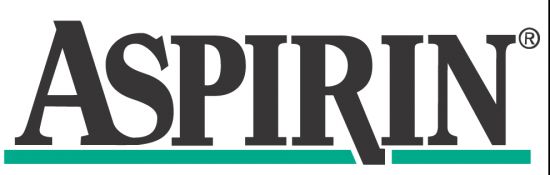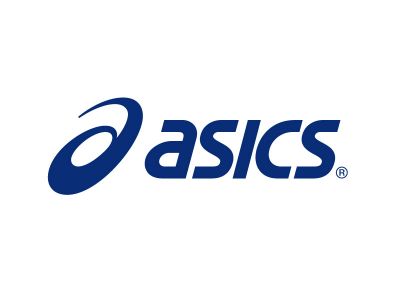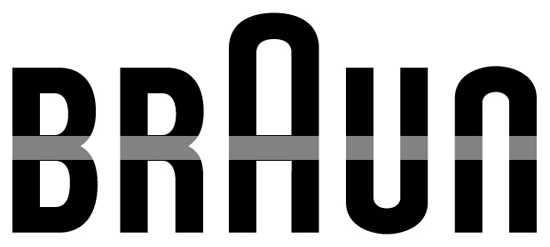
Neue Runde Typo-Quizz gefällig?
Gothaer Versicherungen?
Das ist natürlich richtig.
eine deutsche Marke/Produkt, ist bis heute das weltweit mit Abstand meistverkaufte, in seiner Klasse.
Nachschlag:
Hier nun ein etwas größerer Ausschnitt:
Die Farben wurden nicht manipuliert.
Stutzen, Unter die Schuhe gucken … LLOYD!
Ich hab ja überlegt, ob ich mal wieder nen Buchstaben vorstellen soll, habe mich dann aber doch für eine Marke entschieden, natürlich eine solche, die ich mehrfach pro Woche in Händen halten sollte:
Die Farben sind original, aber auch im Original recht flexibel.
Erster Hinweis: Das Logo, wahrscheinlich ist es eher eine Wortmarke, ist vor Kurzem neu gestaltet worden. Lange Zeit sah der Ausschnitt noch so aus:
Hoffentlich ist es jetzt nicht zu einfach.
"ic" ?
Ja, richtig, aber nicht der InterCity.
Yep, die haben sich ein Redesign verpasst, das kaum noch wiederzuerkennen ist, finde ich.
Oh, ich bin dran, das Blöde ist, dass ihr dies noch niemals in den Händen hattet, vermute ich,
sondern höchstens aus den Augenwinkeln beobachtet habt.
Hier ein weiterer fieser Ausschnitt,
und sachdienliche typografische Hinweise:
– der zugehörige Schriftzug hüpft in der DIN-Klassifikation in die Gruppe fünf
– der Slogan ist aus der City von Georg Trump (jedenfalls auf der Webseite)